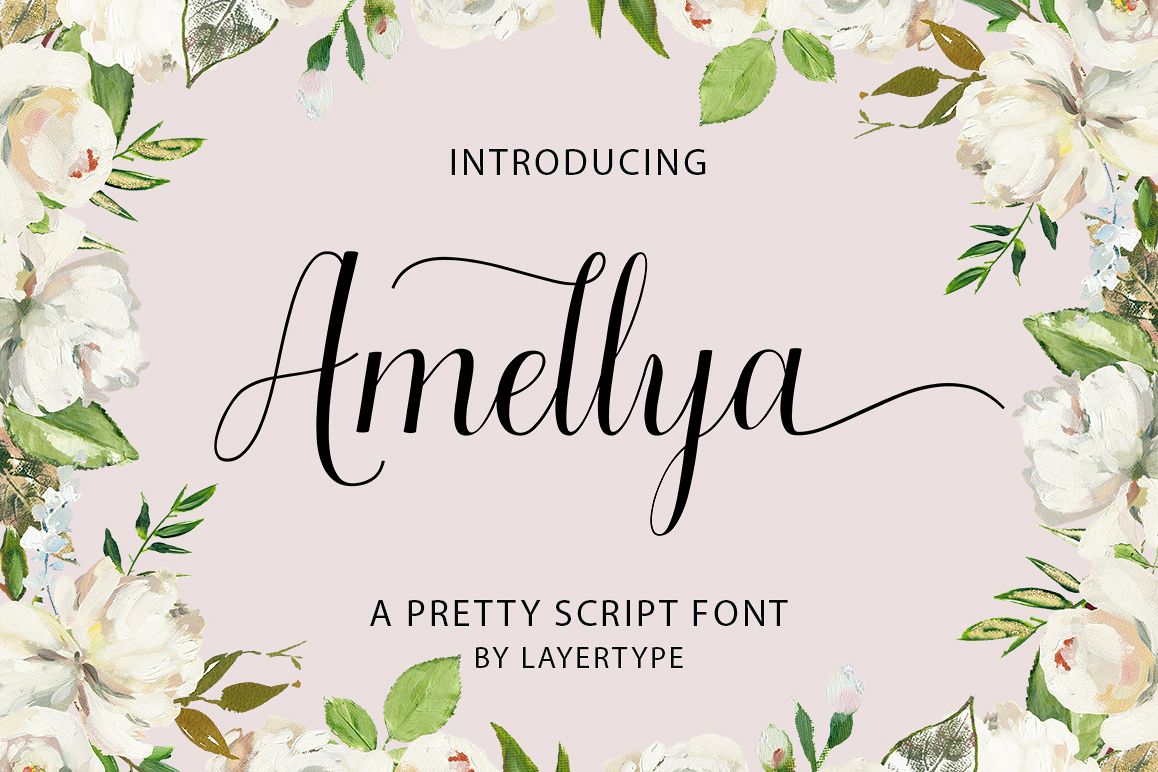
Amellya Script
AmellyaScript-Regular
Amellya Script adalah font skrip modern baru dengan garis dasar tidak teratur. Gaya trendi dan feminin. Amellya terlihat cantik di undangan pernikahan, kartu ucapan terima kasih, kutipan, kartu ucapan, logo, kartu nama dan banyak lagi. Sempurna untuk digunakan dalam tinta atau cat air. Termasuk huruf awal dan akhir, alternatif, pengikat dan dukungan banyak bahasa.